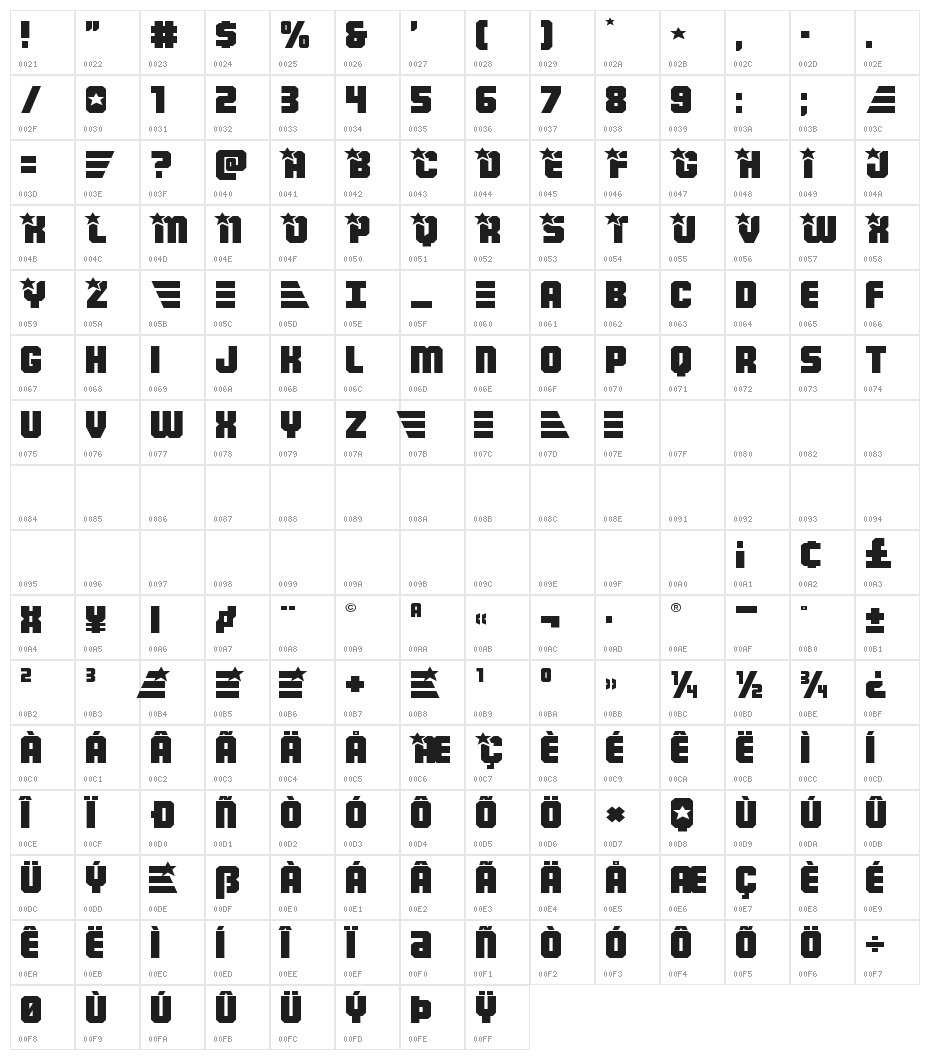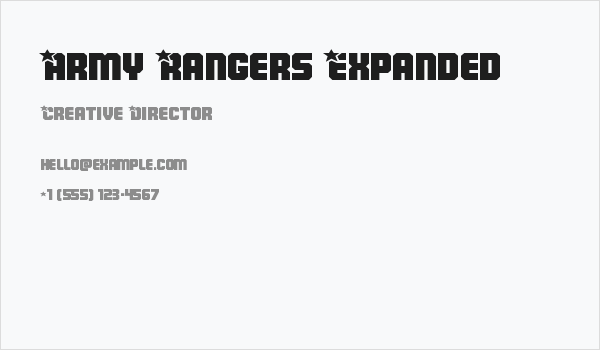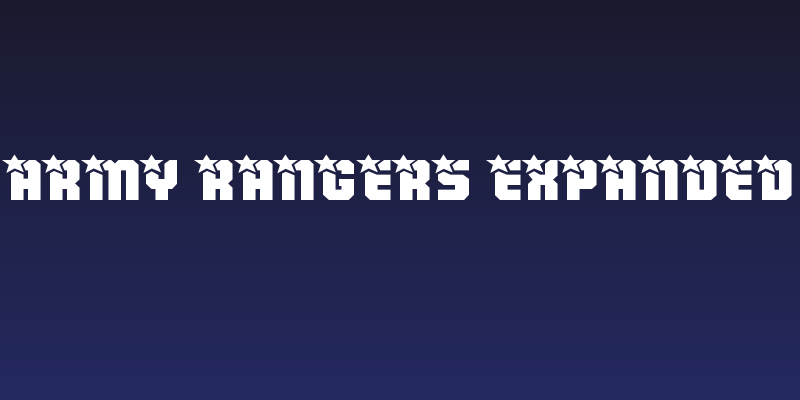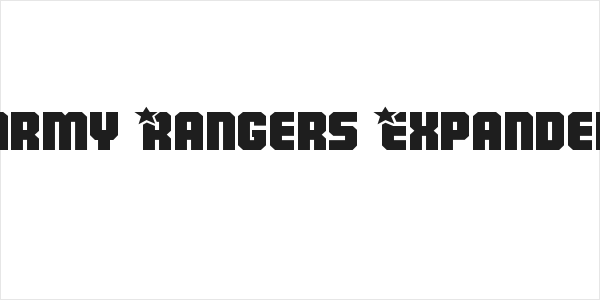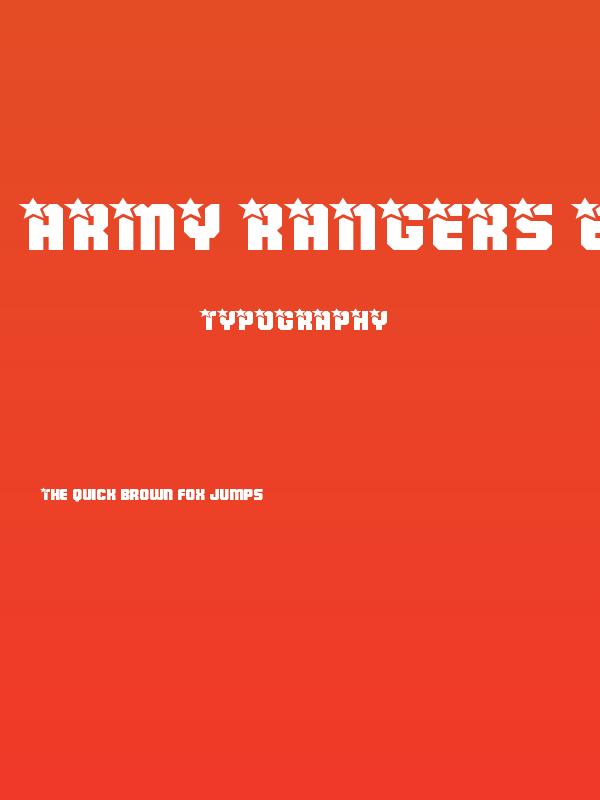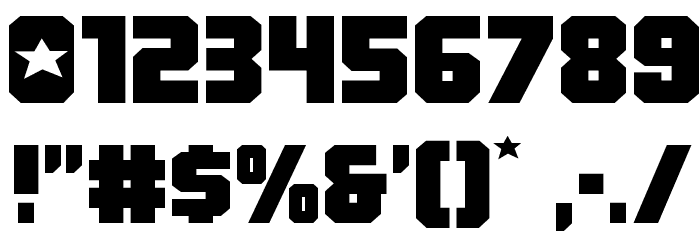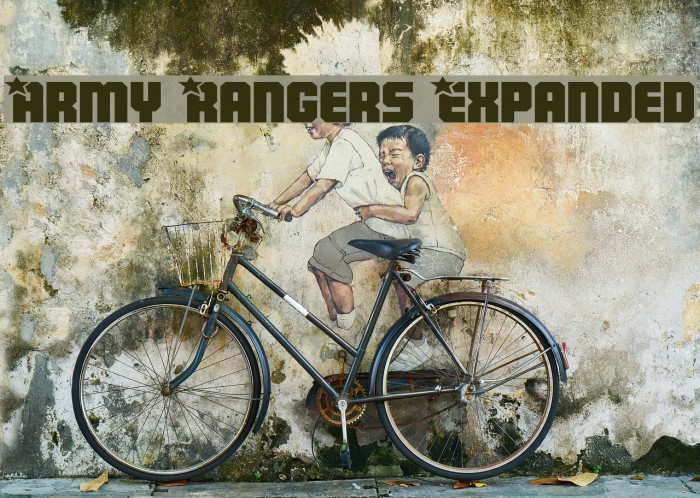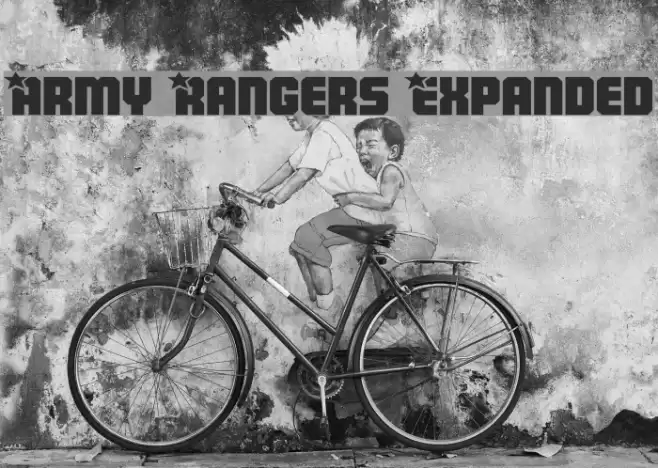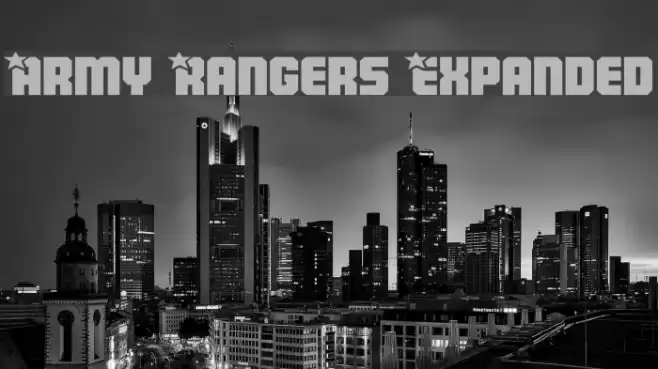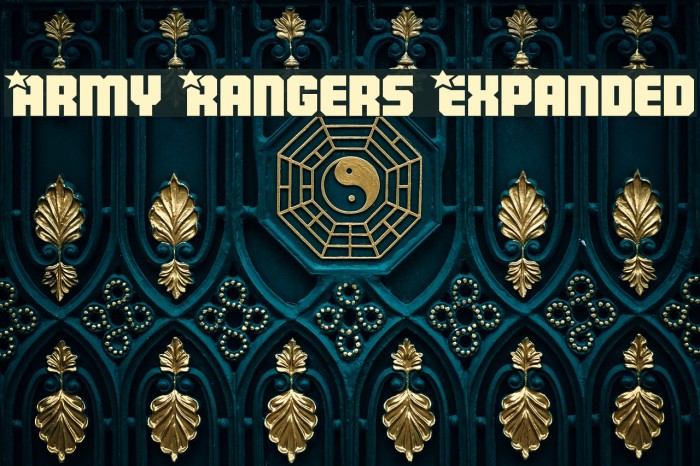
Army Rangers Expanded Font
| Gewicht | Expanded |
| Vorgeschlagene Projekte | Ideal for military-themed posters, patriotic branding, sports team logos, or any project requiring a strong, authoritative typeface. |